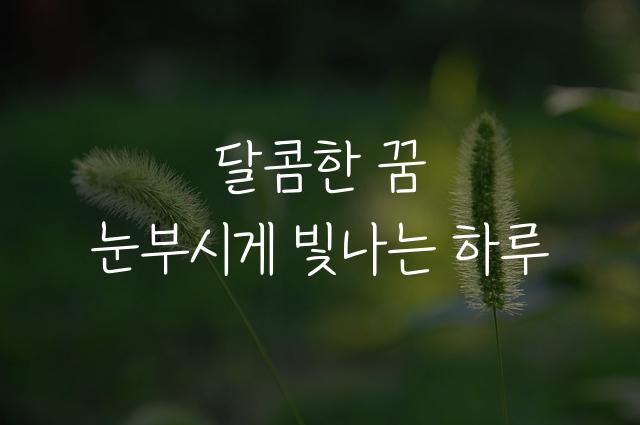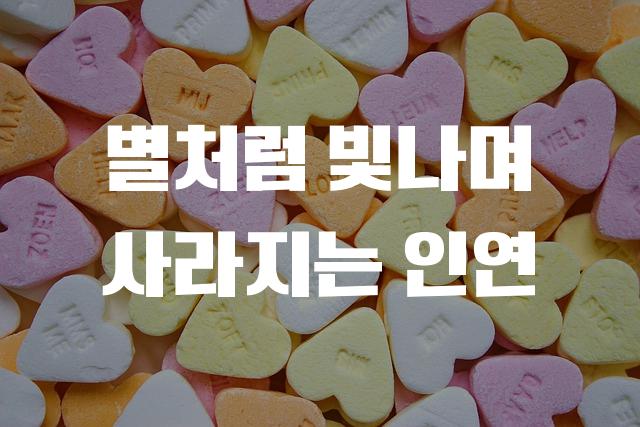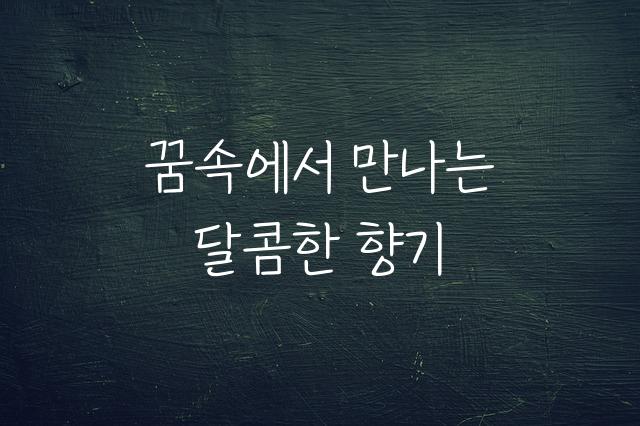
오방주체는 연제구상권활성화재단에서 제작한 한글 폰트로, 또박또박하고 어른스러운 손글씨 느낌을 재현하였습니다. 이 폰트는 전통과 현대가 어우러진 디자인으로, 가독성과 개성을 모두 갖추었습니다.
오방주체은(는)
손글씨, 감성적인, 부드러움 계열의 생김새를 가지고 있으며
초대장, 인사말 카드, 간판 등에서 자주 활용되며, 효과적인 메시지 전달에 적합합니다.
이 폰트는 문화/예술, 이벤트/웨딩, 관광/여행 분야에 잘 어울리며,
전통적, 편안한, 클래식한 느낌을 담고 있는 것이 특징입니다.